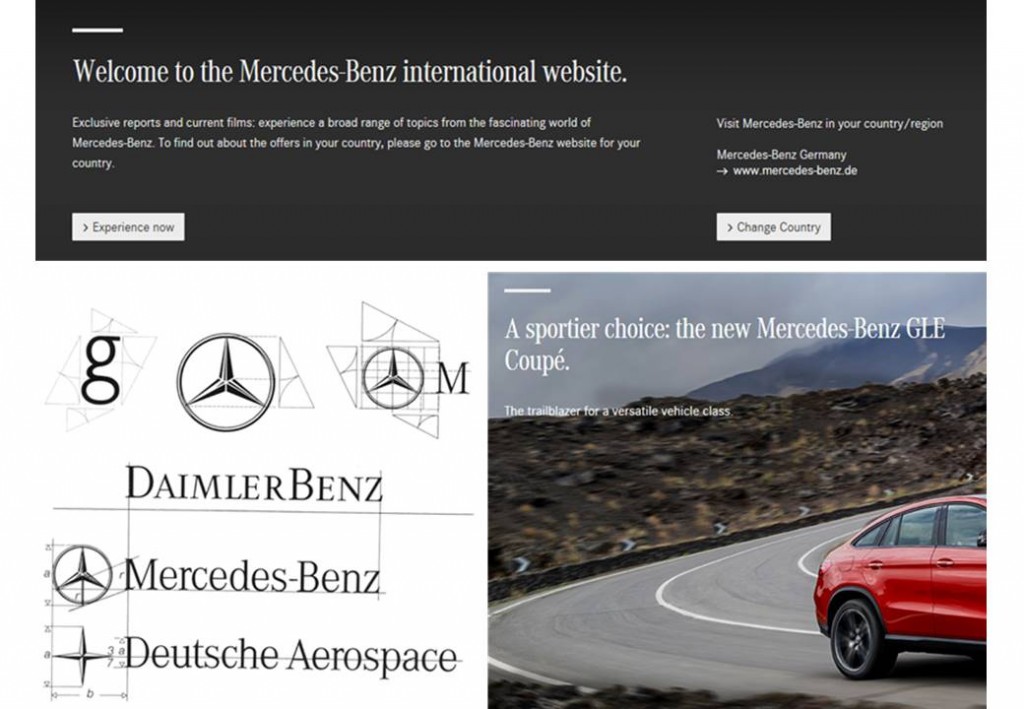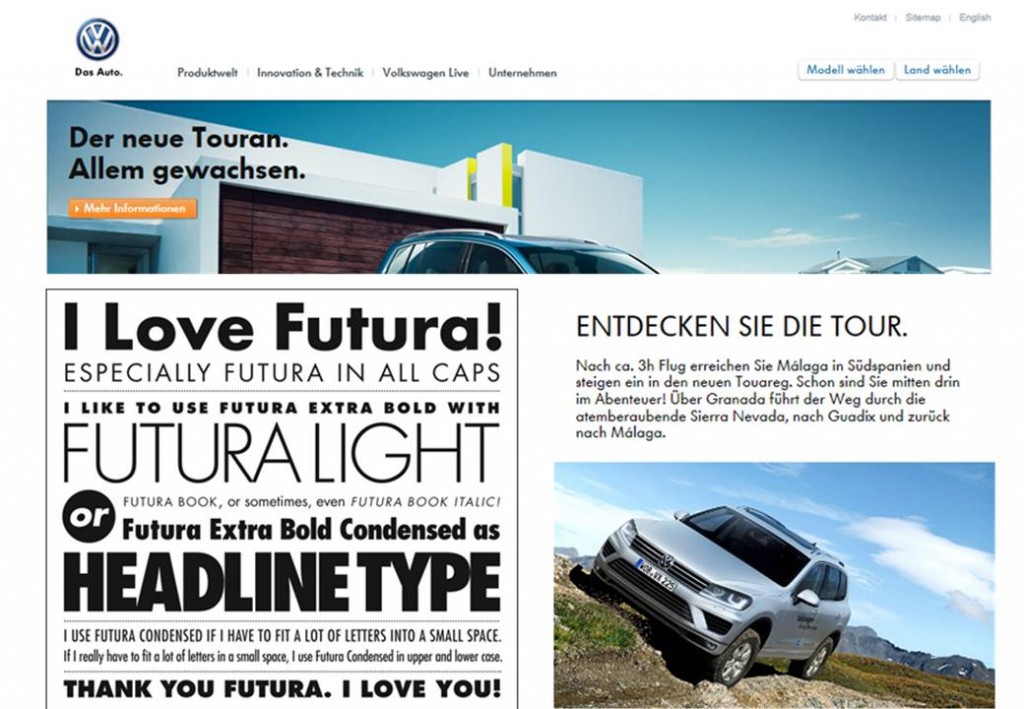
타이포브랜딩 : 왜 전용서체가 필요한가?
타이포브랜딩은 타입(서체)을 통한 기업의 차별화된 브랜딩 활동을 의미합니다. 기업의 독창적인 아이덴티티를 서체로 표현함으로써, 기업의 모든 브랜딩과 마케팅 활동에 보다 효과적인 전략을 가능하게 합니다. 수십 년, 또는 그 이상을 성공적인 브랜드로 자리매김하고 있는 유명 브랜드의 커뮤니케이션 활동에서 주목해야 할 것은 바로 그 브랜드만의 전용서체입니다.
타이포브랜딩 : 왜 전용서체가 필요한가?
목소리로 사람을 기억하고 음색으로 가수를 기억하듯, 우리는 누군가를 목소리로 기억하는 경우가 많습니다. 자신만의 목소리가 없는 사람과 자신만의 목소리가 있는 사람. 누가 더 기억에 남을까요?
얼굴을 몰라도? 목소리를 안다면!
기업 전용서체를 쓴다는 것은, 누구도 사용하지 않는 자신만의 목소리를 갖게 되는 것과 같습니다. 폰트만으로 기업을 기억하고 이미지를 떠올릴 수 있다면 더욱 의미있는 관계가 되어 강력한 커뮤니케이션을 할 수 있습니다. 다양한 컨셉의 수많은 광고와 프로모션을 진행하면서도 기업 전용서체를 통해 일관된 브랜딩을 구축한다면 그 효과를 극대화할 수 있습니다.
기업의 브랜딩이나 광고와 마케팅을 준비하고 있다면, 기업의 목소리부터 찾아보세요. 아마 그게 가장 먼저 필요할지도 모릅니다. 목소리 없이 말을 할 순 없습니다.
봉투 하나부터, 모두가 브랜딩
“Type + Branding = Typo-Branding”
타이포브랜딩은 그래서 필요합니다. 타이포브랜딩은 타입(서체)을 통한 기업의 차별화된 브랜딩 활동을 의미합니다. 기업의 독창적인 아이덴티티를 서체로 표현함으로써, 기업의 모든 브랜딩과 마케팅 활동에 보다 효과적인 전략을 가능하게 합니다. 수십 년, 또는 그 이상을 성공적인 브랜드로 자리매김하고 있는 유명 브랜드의 커뮤니케이션 활동에서 주목해야 할 것은 바로 그 브랜드만의 전용서체입니다.
기존 서체를 커스터마이징한 전용서체를 사용하는 루이비통
한 사회가 소통을 위해 약속한 언어는 문자로 읽혀짐과 동시에 보여집니다. 조금씩 다른 모양과 굵기, 비례, 디테일 등의 디자인에 따라 구별되는 수많은 서체들이 있고 이를 통해 같은 의미이지만 제각기 다른 옷을 입혀 전혀 다른 인상을 줄 수도 있습니다. 기업이나 브랜드의 전용서체는 바로 이런 시각 디자인의 시작이자 완성이라 할 수 있습니다. 그 매체가 온라인이든 오프라인이든 웹사이트든 신문이나 잡지 광고든 그 어디든간에 시각적으로 일관된 디자인을 통해 컨셉과 메시지를 전달하고 브랜드의 아이덴티티를 형성해 나가는 것입니다. 즉 타이포브랜딩은, 브랜드의 목소리를 만들어주는 것입니다.
타이포브랜딩의 대표적 사례
메르세데스 벤츠는 일찍이 전용서체의 필요성을 인식하고 1990년에 코퍼레이트 A(Coporate-A)를 개발하였습니다. 코퍼레이트 A 서체는 한글의 명조체에 해당하는 스타일로 날씬한 비례와 유려한 형태, 날카로운 획 마무리 등이 최고를 지향하는 브랜드의 이미지를 잘 대변해줍니다.
독일 자동차 폭스바겐은 1960년대 이후 ‘푸투라(Futura)’라는 서체를 커뮤니케이션에 사용해 왔습니다. 푸투라는 1927년 독일의 모더니즘을 반영해 디자인된 서체로 원, 삼각형 등의 원초적인 형태를 바탕으로 전체 알파벳을 디자인 했습니다. 따라서 군더더기 없는 기능적 형태가 특징입니다.
이러한 역사적 배경과 형태적 특징은 폭스바겐의 탄생 배경, 우수한 기능, 친근감을 주는 곡선 형태 등과 완벽한 궁합을 이루며 폭스바겐이라는 브랜드를 구성하는 목소리 역할을 톡톡히 해오고 있습니다.
1984년, 애플이 IBM이 지배하던 컴퓨터 시장에 도전장을 내면서 사용했던 전용서체는 ‘애플 게라몬드(Apple Garamond)’였습니다. 한글로 치면 본문에 보편적으로 사용되는 명조체를 현대적 감각에 맞춰 날씬하게 변형한 형태 입니다. 그러나 2001년, 애플은 아이팟을 출시하면서 혁신적 제품에 걸맞는 시각적 커뮤니케이션을 위해 로고와 전용서체 등을 새롭게 바꿨습니다.
현재는 ‘미리아드(Myriad)’라는 한글 고딕체에 해당하는 양식의 서체를 사용해 간결한 디자인 속에 최대한의 기능을 내포한 애플사의 제품들과 그 이미지를 나타내고 있습니다.
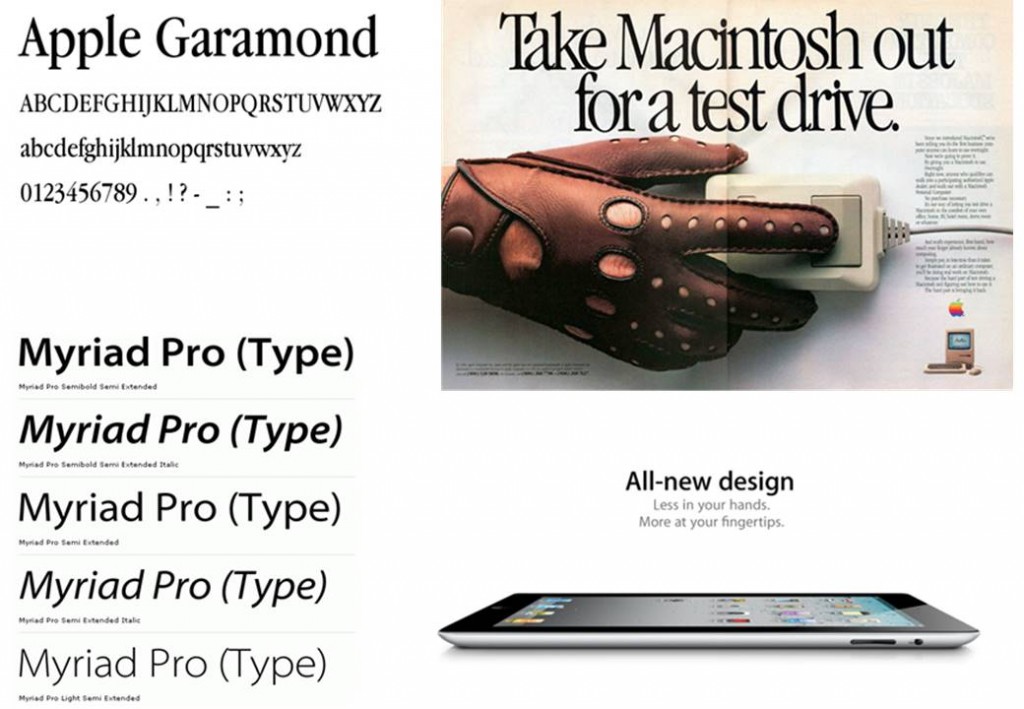
애플의 전용서체 사용 예시
지금까지 타이포브랜딩이란 무엇이며 왜 필요한지, 또한 그 대표적인 사례들을 설명해드렸습니다. 벤츠, 폭스바겐, 애플의 전용서체가 좀 다르게 보이시나요? 그들의 뚜렷한 목소리가 이제는 들리시나요? 이것이 바로 타이포브랜딩입니다.